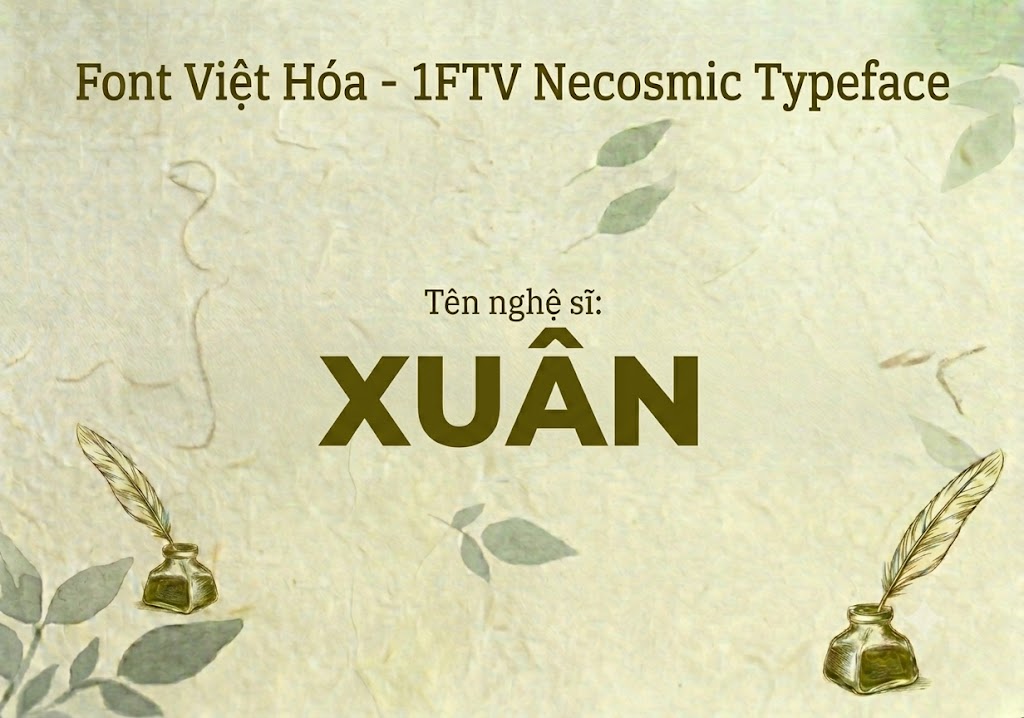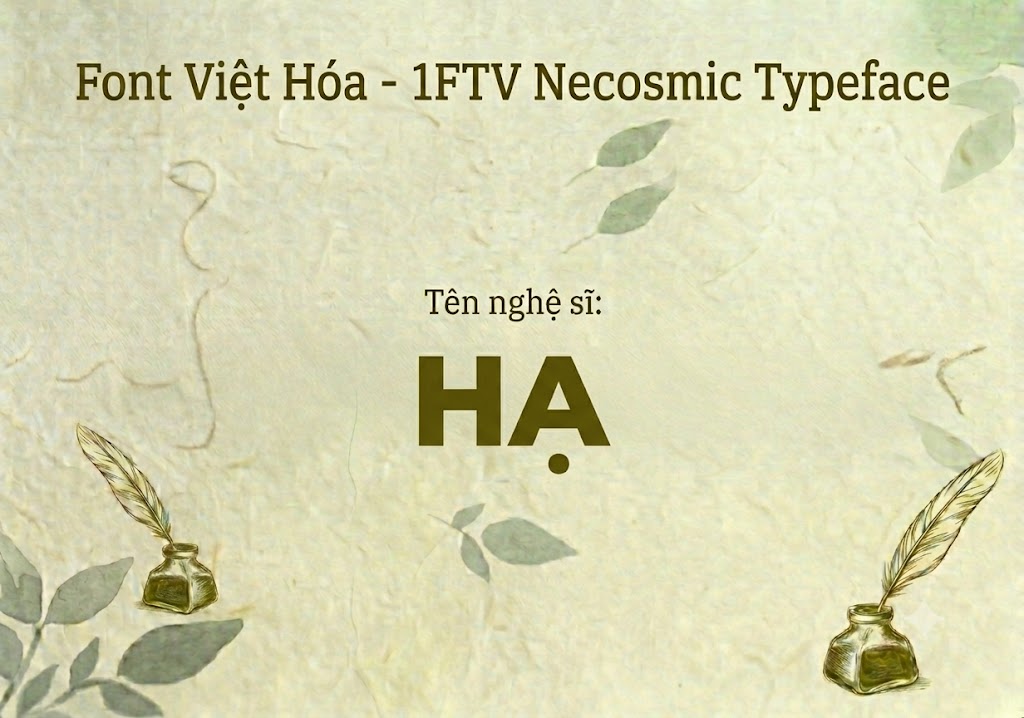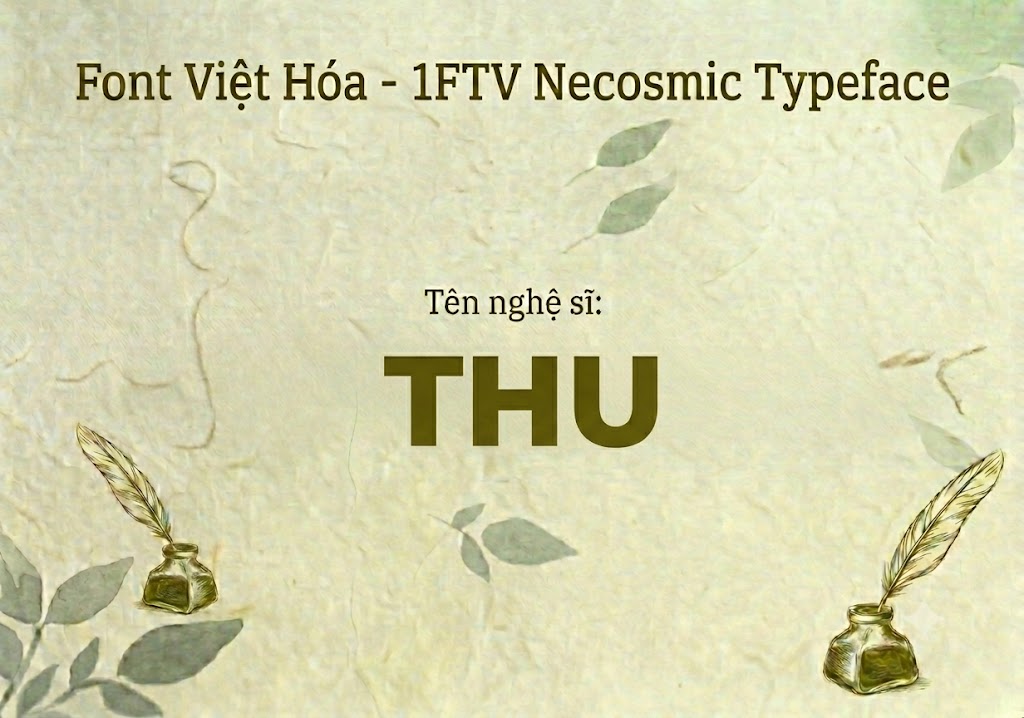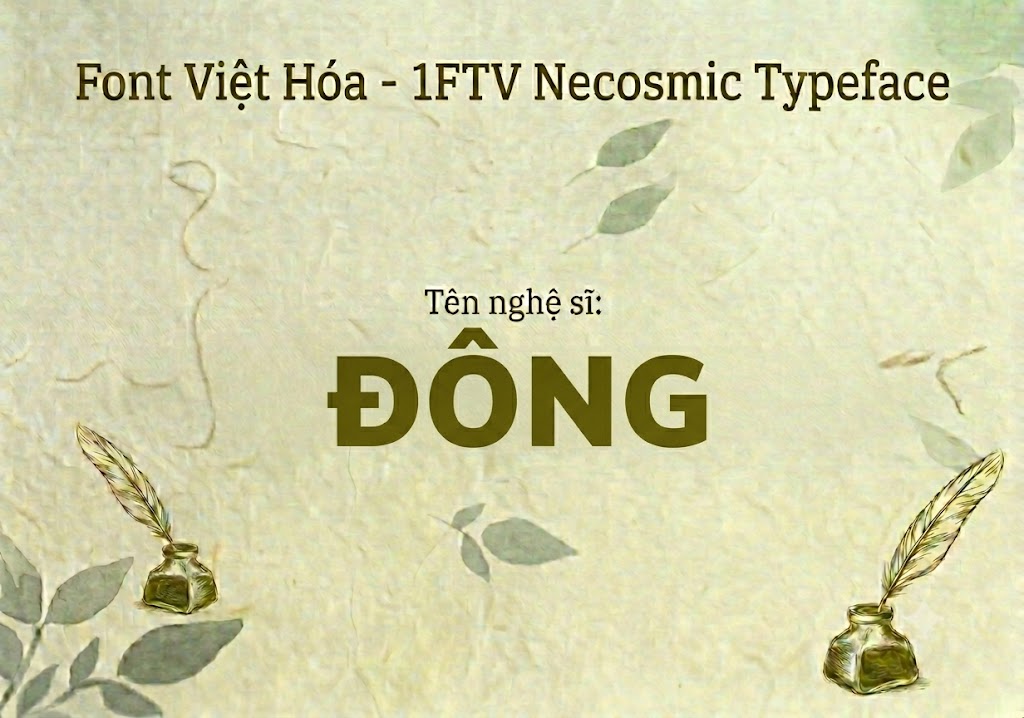
1FTV Necosmic
Trong kỷ nguyên sáng tạo nội dung số, các phông chữ mang phong cách cyberpunk, vũ trụ hay công nghệ tương lai đang trở thành xu hướng dẫn đầu.
Những kiểu chữ này mang lại một cảm giác hiện đại, đậm chất khoa học viễn tưởng và kích thích thị giác cực mạnh cho người xem.
Nếu bạn đang muốn tìm kiếm một giải pháp thiết kế làm tiêu đề video ngắn, banner gaming hay poster công nghệ độc lạ, thì font 1FTV Necosmic chính là lựa chọn hoàn hảo.
Giới thiệu về font 1FTV Necosmic
Font 1FTV Necosmic là một phông chữ display không chân mang phong cách không gian kĩ thuật số và công nghệ tương lai đầy ấn tượng.
Nhờ các thông số kĩ thuật tối ưu này, phông chữ có khả năng hiển thị sắc nét tuyệt đối trên mọi nền tảng đồ họa hiện đại mà không lo bị lỗi vỡ nét.
Đặc điểm nổi bật của phong cách thiết kế Necosmic
Sức hút khác biệt của font 1FTV Necosmic đến từ sự kết hợp giữa phom chữ hình khối vuông vắn và những góc bo tròn kĩ thuật số mềm mại.
Các ký tự được cách điệu theo xu hướng thiết kế viễn tưởng, mô phỏng các đường mạch điện tử hoặc cấu trúc cơ khí của các tàu không gian.
Điểm bứt phá lớn nhất nằm ở các đường cắt góc táo bạo trên các chữ cái như A, E, G, H, tạo nên những khoảng hở stencil đầy nghệ thuật.
Phông chữ được xây dựng hoàn toàn theo cấu trúc all-caps đồng đều, giúp bạn dễ dàng sắp xếp các dòng tiêu đề gọn gàng, cân đối mà không sợ bị lệch cao độ.
Để phông chữ vận hành mượt mờ trên hệ thống máy tính, phiên bản font 1FTV Necosmic đã trải qua quy trình xử lý thông số kĩ thuật kỹ lưỡng.
Hệ thống khoảng cách chữ và độ giãn dòng đã được căn chỉnh chuẩn xác, giúp các từ khi đứng cạnh nhau luôn giữ được khoảng trống thẩm mỹ.
Bên cạnh hệ thống chữ cái viết hoa đồng bộ, phông chữ còn tích hợp đầy đủ dãy số từ 0-9 cùng các ký tự đặc biệt, dấu câu thông dụng (.,;: ' " (!?) +-*/=).
Tiện ích này giúp bạn thoải mái biên tập nội dung quảng cáo hay làm sub video mà không lo bị lỗi hiển thị hay thiếu ký tự khi gõ.
Hình ảnh demo thực tế của font 1FTV Necosmic
Để giúp bạn dễ dàng hình dung khả năng co giãn và hiển thị linh hoạt của phông chữ này trên các kích thước khác nhau, hãy cùng xem qua bảng mô phỏng thực tế:
Kích thước nhỏ (12pt – 24pt): Các nét chữ công nghệ và khoảng cách mở rộng vẫn giữ được sự rõ ràng, dễ đọc trên màn hình điện thoại di động.
Kích thước lớn (36pt – 72pt): Đây là không gian lý tưởng để font chữ phô diễn toàn bộ sức mạnh hình khối không gian, tạo hiệu ứng thị giác cực ngầu cho các tiêu đề chính.
Ứng dụng của font Necosmic trong thiết kế đồ họa và làm video
Sở hữu nét cá tính bứt phá và mang đậm chất tương lai, font 1FTV Necosmic mở ra không gian ứng dụng rộng lớn cho các dự án marketing và truyền thông:
Thiết kế thumbnail Youtube và ảnh thu nhỏ mạng xã hội: Đây là vũ khí tuyệt vời cho các video thuộc chủ đề gaming, esports, review đồ công nghệ hoặc khoa học đời sống.
Làm tiêu đề video ngắn (Tiktok, Shorts, Reels): Cấu trúc chữ độc lạ này giúp các câu từ khóa chính, tiêu đề mở đầu video trở nên vô cùng bắt mắt và giữ chân người xem lướt chậm lại.
Banner và poster giải đấu hay sự kiện: Hoàn hảo cho các poster giới thiệu sản phẩm công nghệ cao, banner trò chơi điện tử hoặc bìa album nhạc cá tính.
Nhận diện thương hiệu phong cách hiện đại: Phù hợp làm logo dạng chữ khối cho các thương hiệu thời trang techwear, studio sáng tạo hoặc các công ty khởi nghiệp công nghệ.